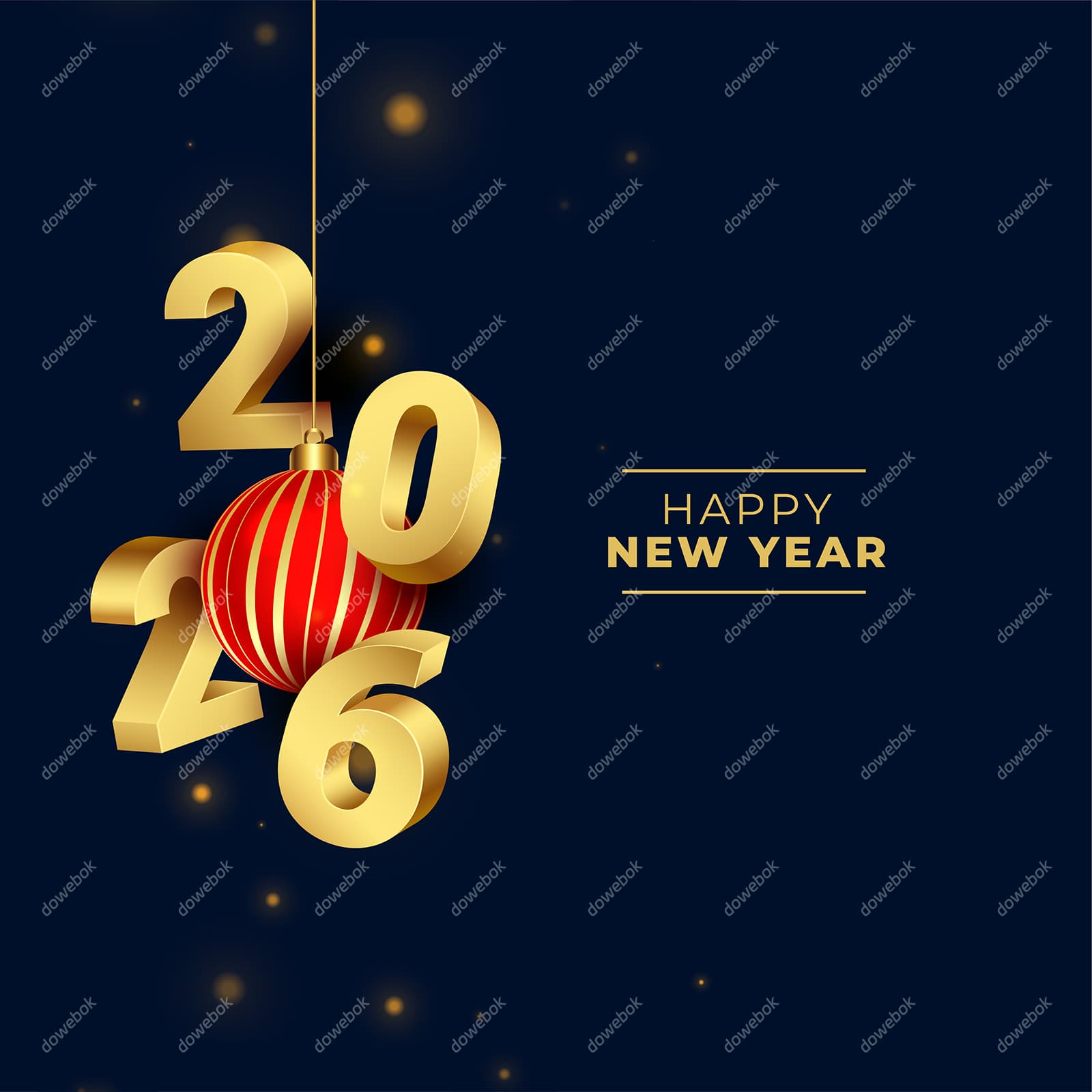
这是一款红色装饰球和金色立体数字设计的 2026 新年快乐矢量素材,深邃藏蓝背景点缀暖光光斑,金色立体 “2026” 字体醒目华贵,数字间嵌着红金条纹装饰球(以金线悬挂),右侧配 “Happy New Year” 金色文字。整体红金与藏蓝碰撞,既借装饰球显节日温馨,又以立体字衬出奢华质感,灵动光斑更添氛围,适配新年贺卡、装饰物料等场景。